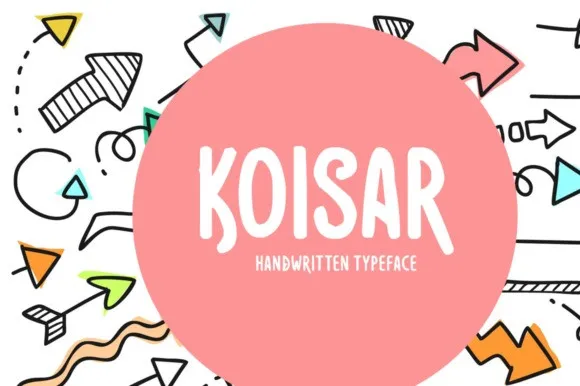
Koisar “Fun Font” – Download Grátis
Este é um estilo que você pode aplicar a muitas de suas memórias caras, esta fonte foi projetada especificamente de uma forma engraçada. A fonte Koisar foi criada e compartilhada pela comunidade de fonts do Instagram. É uma font escrita a mão suave e descontraída, com um toque leve que adicionará uma sensação encantadora a qualquer projeto gráfico. A fonte Koisar Fun é especialmente adequada para uma variedade de necessidades humorísticas, como embalagens de batatas fritas e alimentos, embalagens de snacks divertidas, tags de comida, e até mesmo materiais educativos para crianças. Seja qual seja a sua necessidade criativa em momentos leves e engraçados, Koisar Fun será uma escolha perfeita.